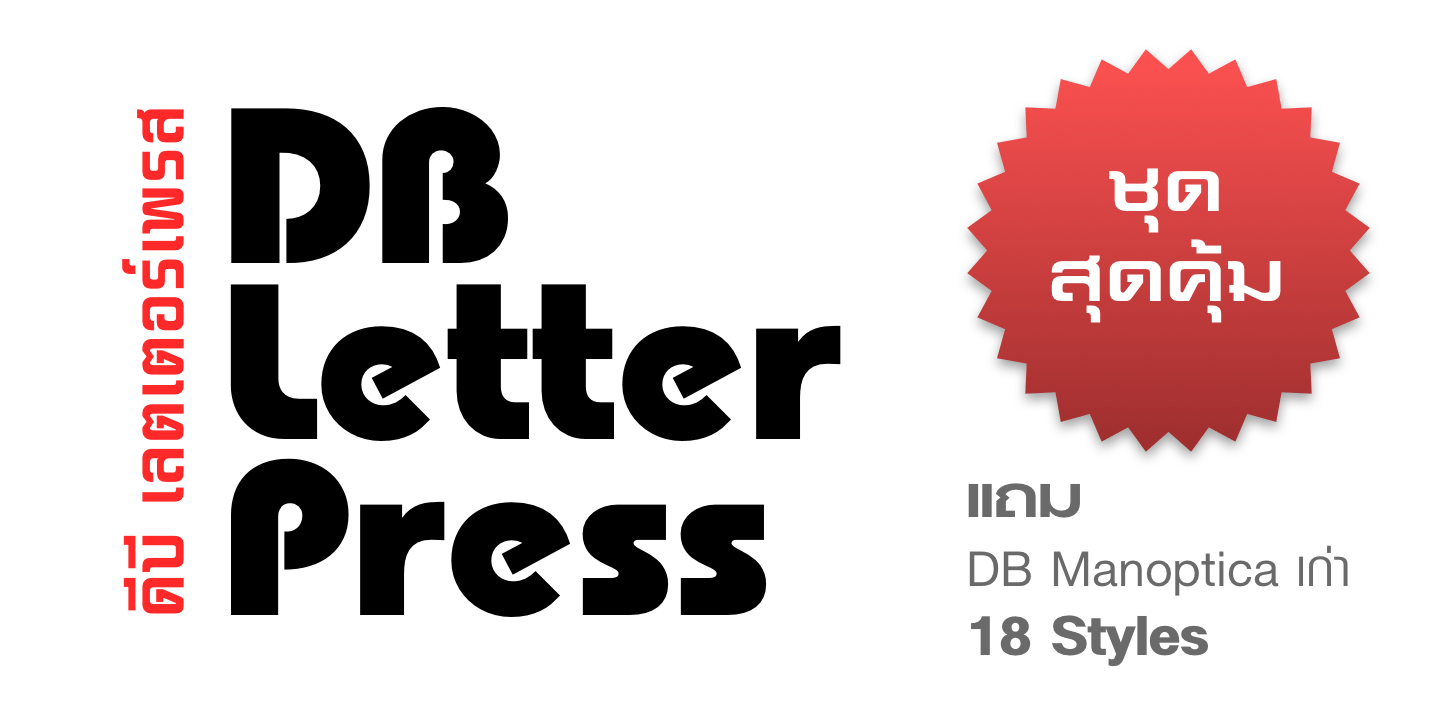
DB Letterpress
ดีบี เลตเตอร์เพรส
15 font families,
82 styles
รวมฟอนต์ใหม่ ทำจากตัวอักษรลอก Letter Press 12 styles ที่ไม่เคยผลิตเป็นฟอนต์ดิจิทัลมาก่อน
ขยายน้ำหนักตัวพิมพ์พร้อมตัวเอนให้เลือกใช้เพิ่ม รวมมากถึง 60 styles!